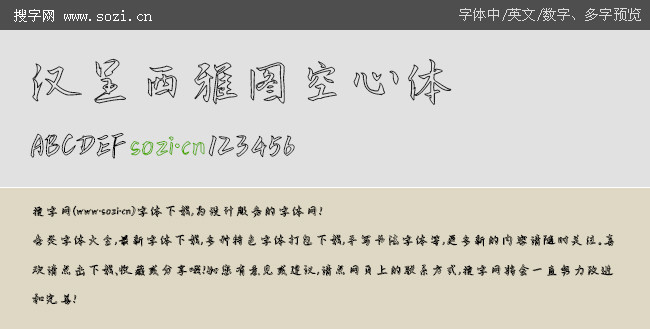
漢呈西雅圖空心體
搜字網(wǎng)給大家提供一款漢呈西雅圖空心體中文字體下載,漢呈西雅圖空心體是由漢呈字體所推出的一款藝術(shù)空心字體。獨(dú)特的空心字體設(shè)計(jì),結(jié)合中國獨(dú)有的書法字體風(fēng)格,非常有設(shè)計(jì)感,很適合用于藝術(shù)設(shè)計(jì)、廣告宣傳、海報(bào)設(shè)計(jì)等應(yīng)用。(本字體為個(gè)人非商用版,如需要商用請(qǐng)聯(lián)系作者購買版權(quán))